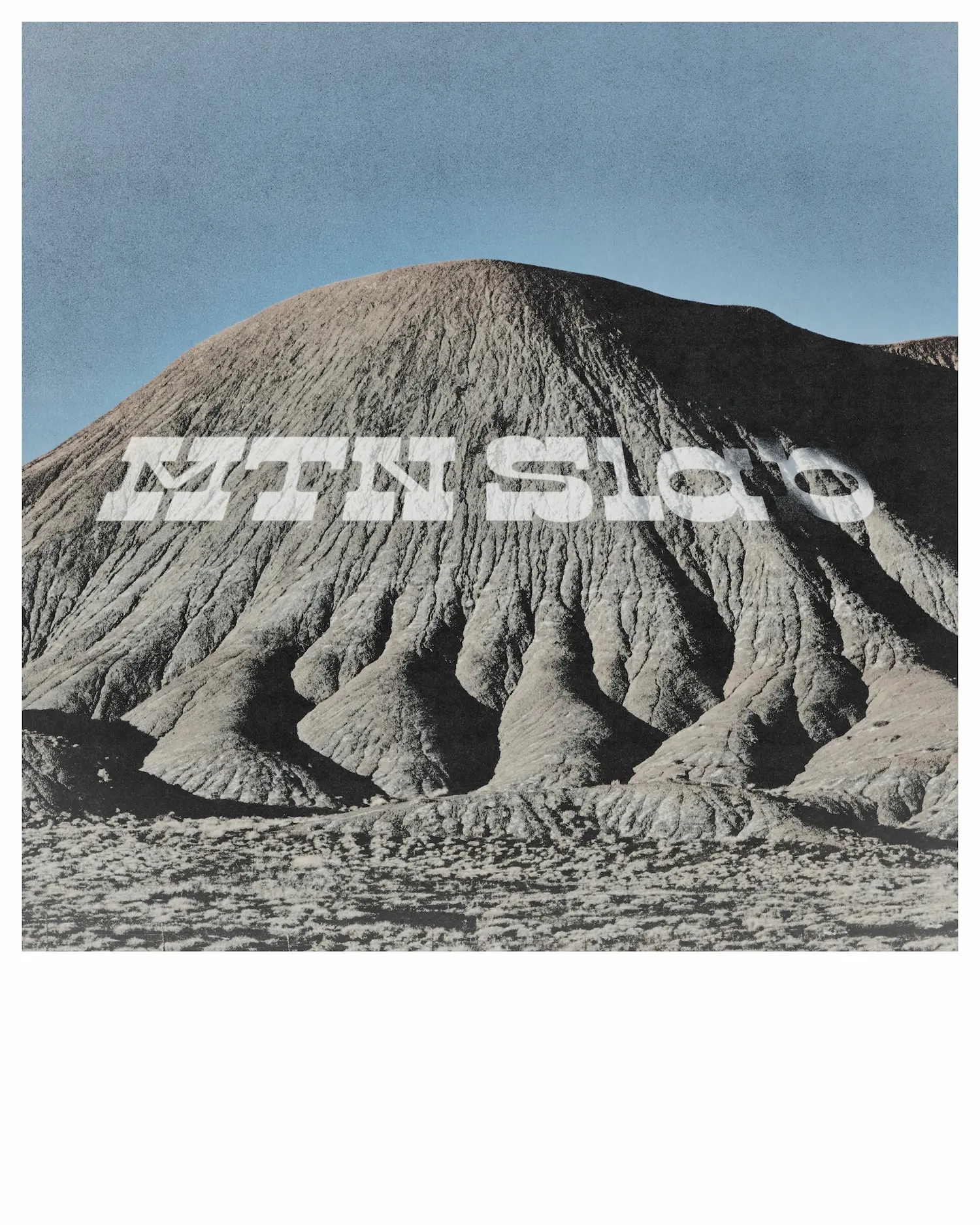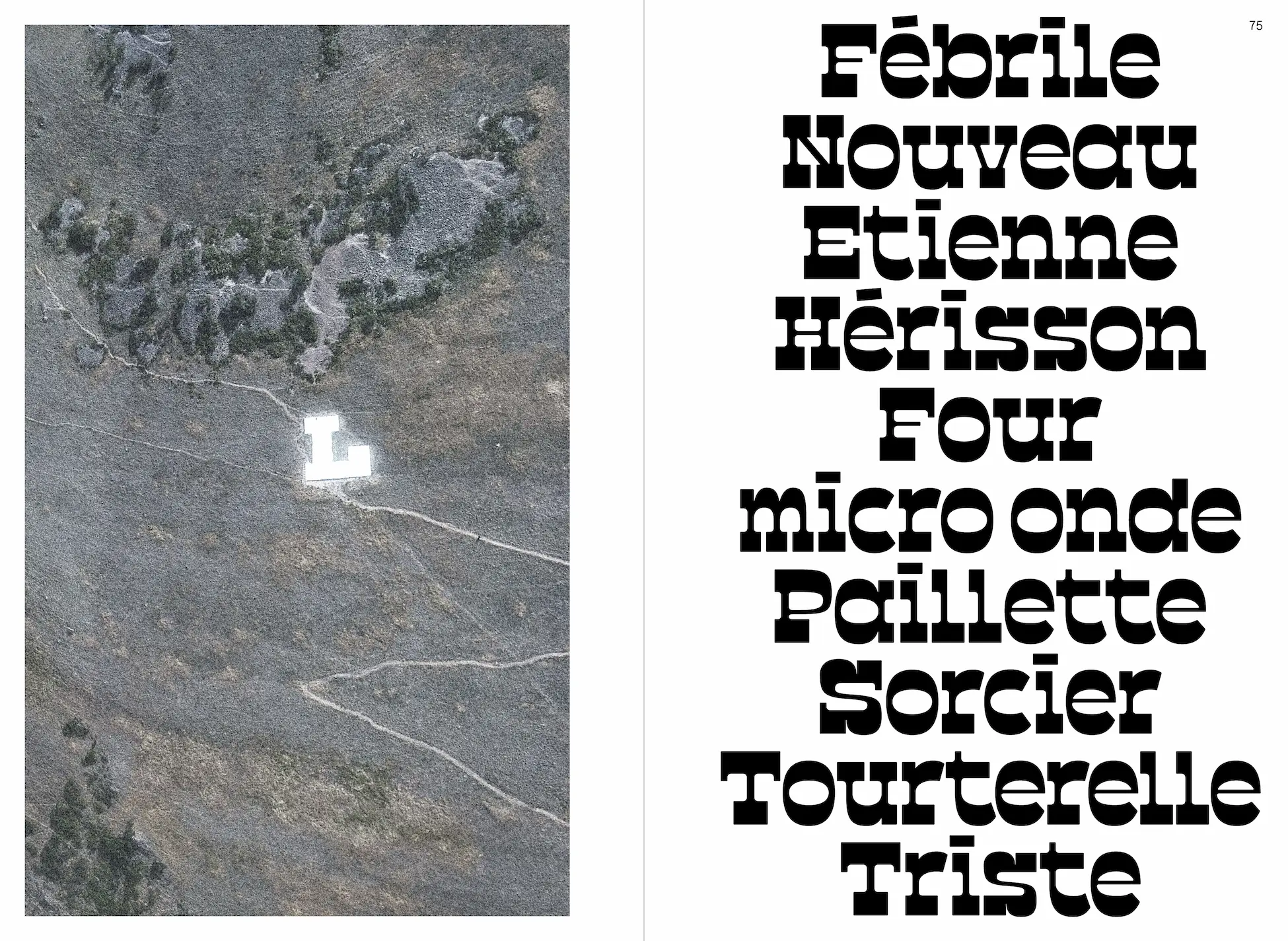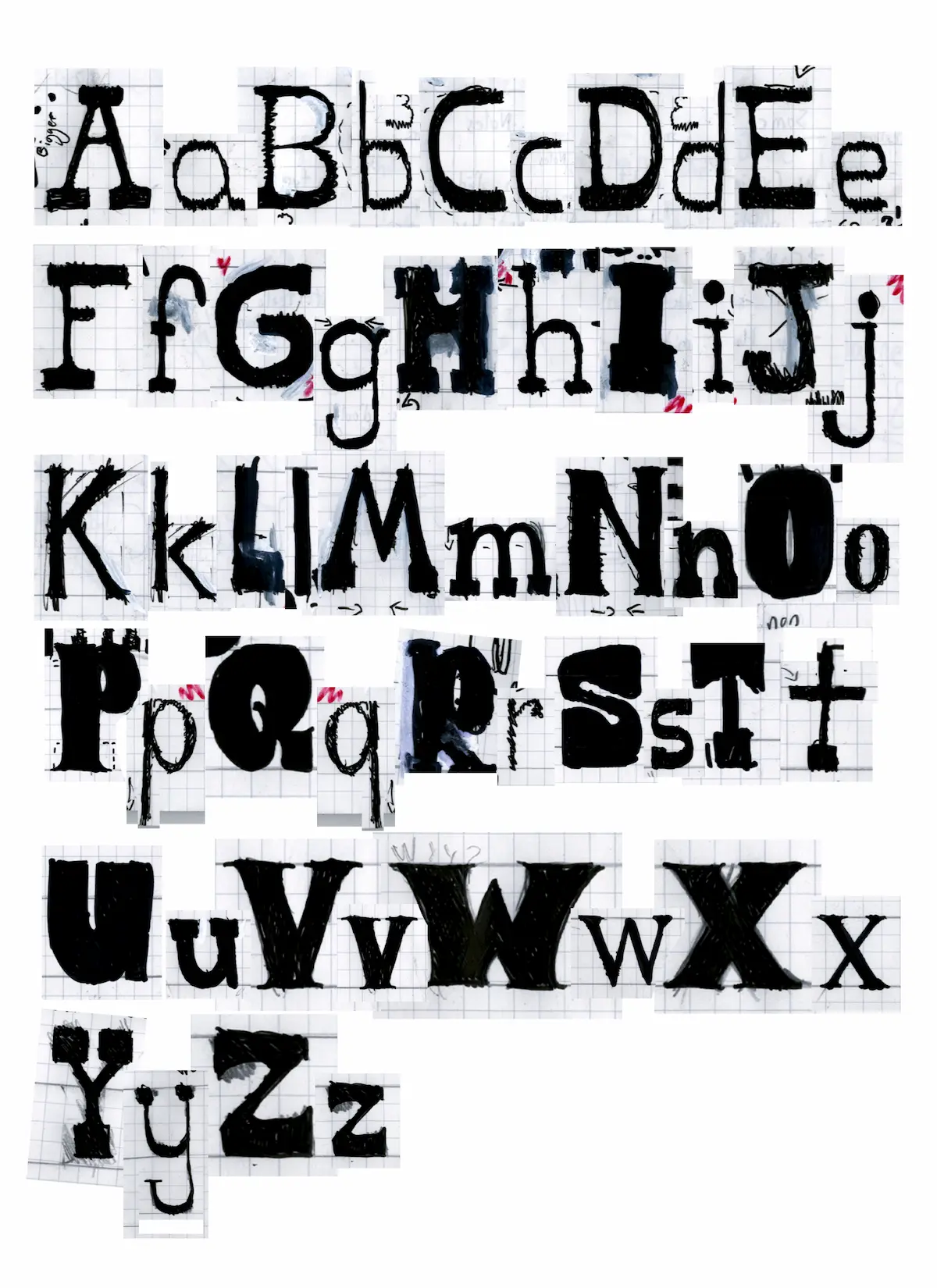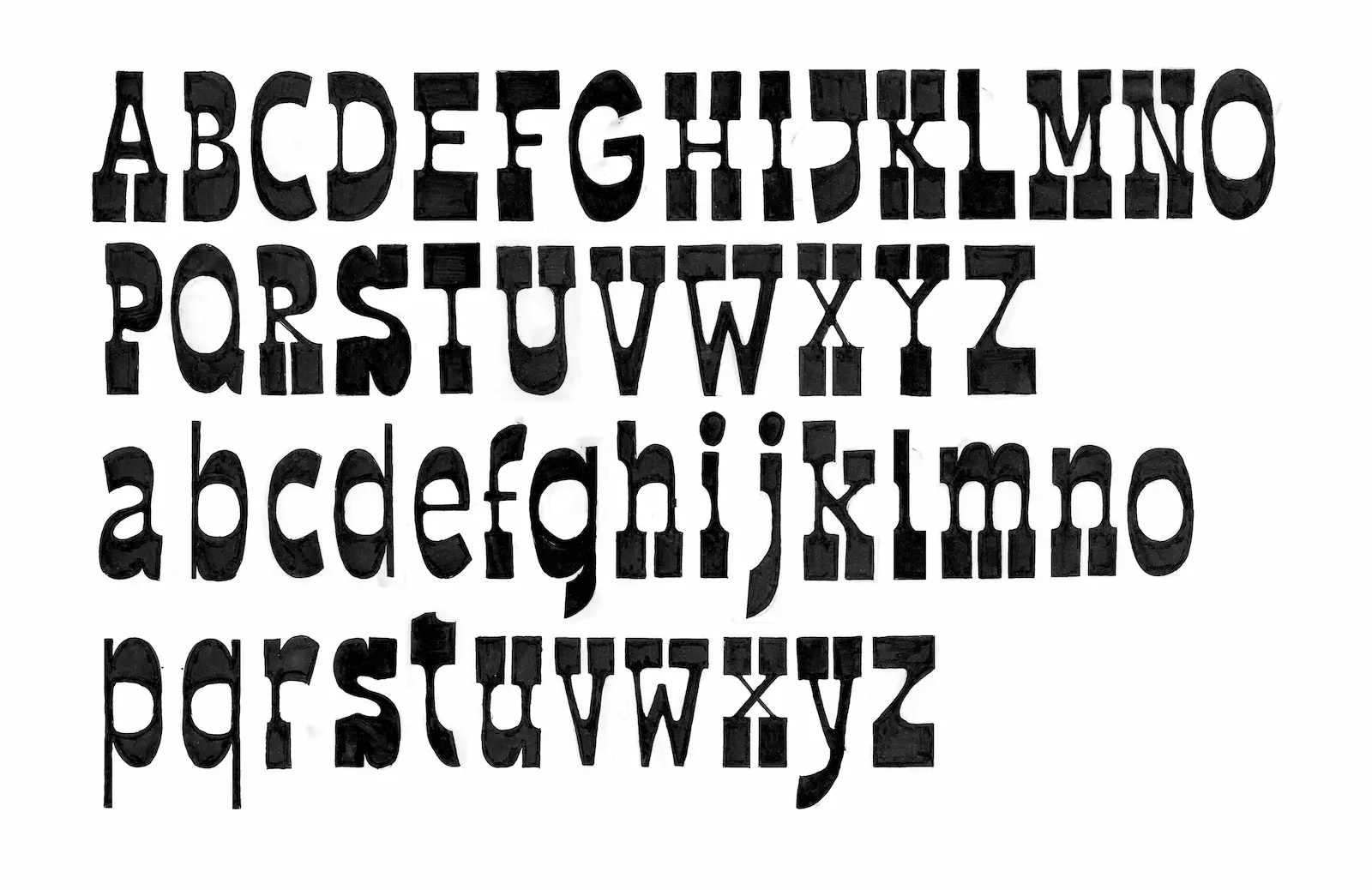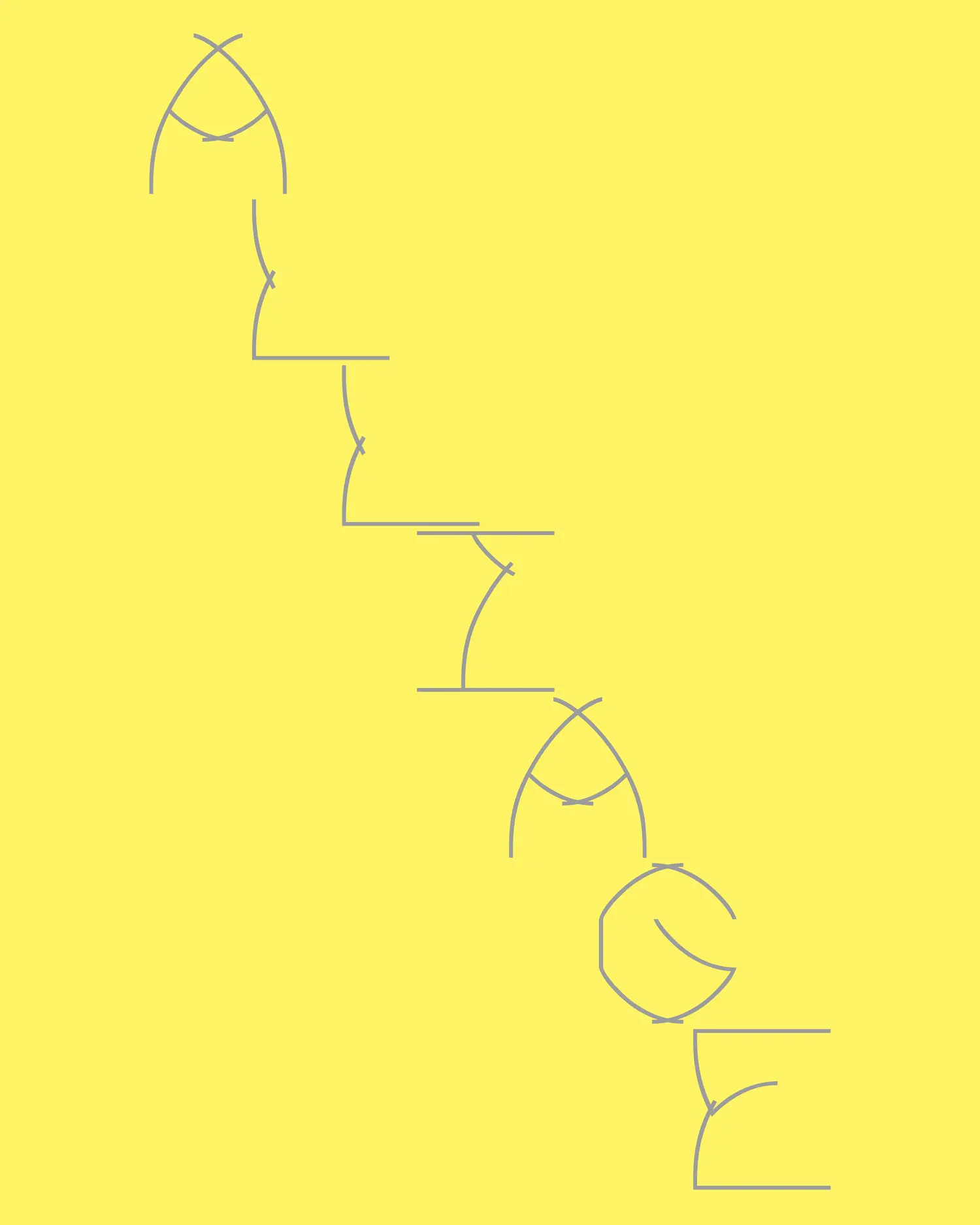
MTN Slab
On peut apercevoir plus de 500 lettres gravées dans les collines de l’ouest des États-Unis. Ces curieux caractères de bord d’autoroutes sont couramment nommés “mountain monograms”. Ils prennent la forme d’abréviations ou de grandes lettres individuelles qui ornent le flanc des collines. Généralement créées et entretenues par des écoles ou des villes, elles constituent une partie importante du paysage culturel de l’Ouest américain. Un mythe suggère que ces lettres de chaux auraient été initialement érigées pour identifier les communautés depuis les airs afin de permettre aux pilotes de larguer du courrier. Ces monogrammes font plutôt office de symbole de fierté scolaire ou d’identité civique. MTN Slab est une slab sérif à contraste inversé inspirée par ces caractères. Elle renvoie autant au côté disparate que forme l’ensemble des monogrammes qu’aux traits caractéristiques des caractères de bois et des slab serif traditionnelles de l’Ouest américain.
• Affiche expérimentale combinant mots en sérif noir et fond texturé rose et gris, illustrant des essais typographiques.
• Gros plan sur une composition typographique bleue, partiellement masquée par des bandes de ruban blanc.
• Page de spécimen montrant paragraphes brouillés, alphabet minuscule et majuscule, accents et chiffres.
• Planche montrant la construction modulaire des chiffres 0 à 9, avec repères et annotations techniques.